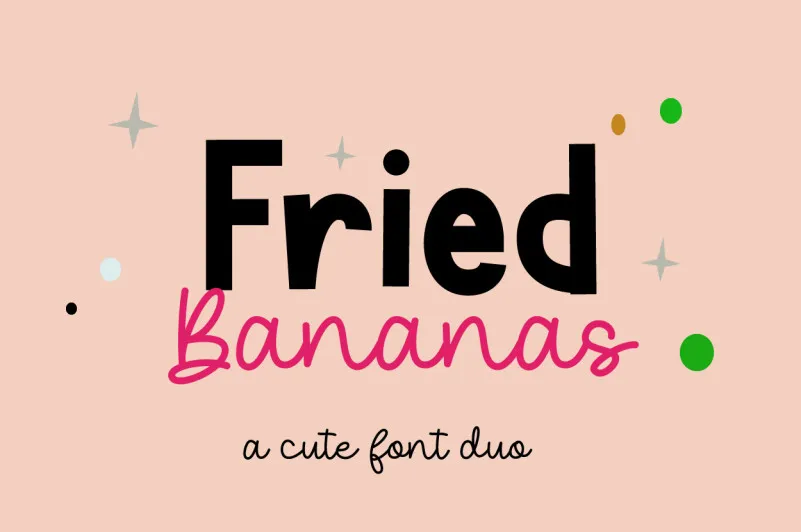
Descubra a riqueza vibrante e arredondada das “Fried Bananas Font”. Sugerida para criativos que buscam uma tipografia com personalidade, esta fonte sem serif é perfeita para qualquer projeto de design web moderno ou gráfico digitado. Sujeito às nossas condições de uso, a instalação e uso desta fonte permitem-lhe explorar formas arrojadas e cores vivas que vão revolucionar o seu design. Inspirada na experiência culinária exuberante da banana frita, esta font não apenas acrescentará um toque tropical e único aos seus projetos, mas também permitirá a você criar design visualmente atraente e memorável. Sua variedade de linhas leves e suavemente curvadas fazem dela uma escolha ideal para texturas digitais, interfaces web e qualquer projeto que valorize o estilo e a criatividade. Instale-a agora e deixe-se embalar pela dança vibrante desta font sem serif.